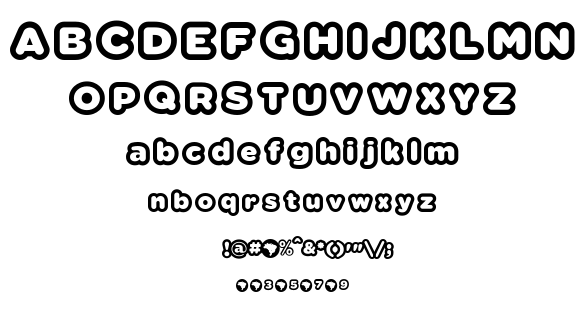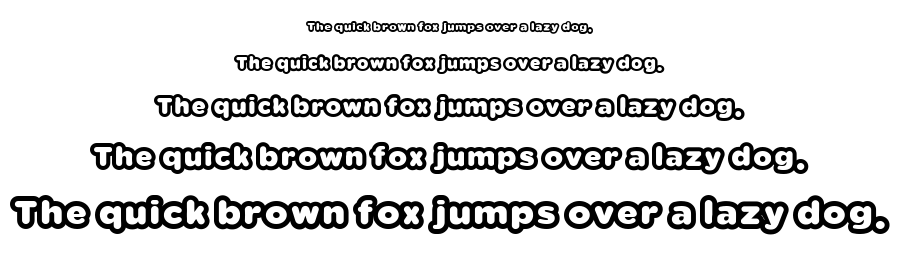
Nueva tipografía vacacional 2015 de formas voluptuosas, gruesas y redondeadas. Fuente de talla baja de carácter amigable con ascendentes y descendentes cortos de fuerte contraste en las uniones de las astas, agradable y funcional para títulos y textos cortos o el diseño de carteles y posters.===========New 2015 Holiday typography voluptuous, thick and rounded shapes. Font of stunting friendly character and falling short of strong contrast in the joints of the antlers, pleasant and functional for titles and short texts or designing posters and affiches.===========• Descarga gratis las versión completa con 405 caracteres desde mi web >> Vacaciones, Display outline & Round font 2015• Números disponibles en mi web.• Sólo para uso personal.• Licencia comercial disponible• Download the full version with 405 characters from my website.• Numbers available on my website.• Only for personal use.• Commercial license available